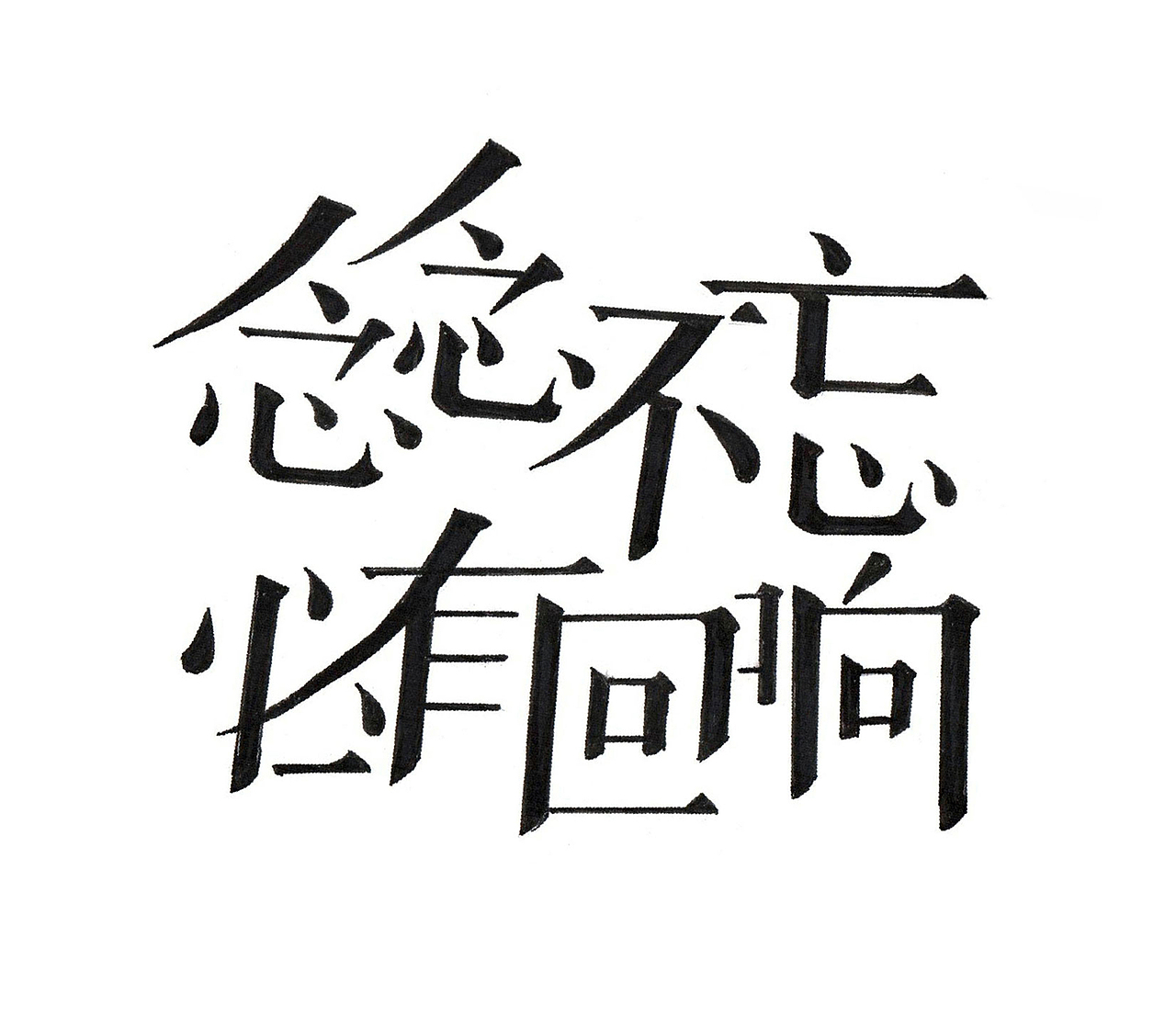
斜体有一种向前的意味,斜体具有的动感和速度感更能体现中心价值。斜体给设计师带来的挑战是空间布局。不少汉字的左右空间是不对称的,就不能简单粗暴地把它弄斜,否则汉字的结构就会不稳,甚至坍塌。所以需要对汉字的左右结构有一个收缩或是放大的微调。另外也需要去调整每个汉字的斜度,看组合的视觉效果,如果生硬地把字弄斜,会感到突兀。每个设计师对稳定、平衡、空间美感的认知都不同,所以需要我们多花时间去学习沟通。